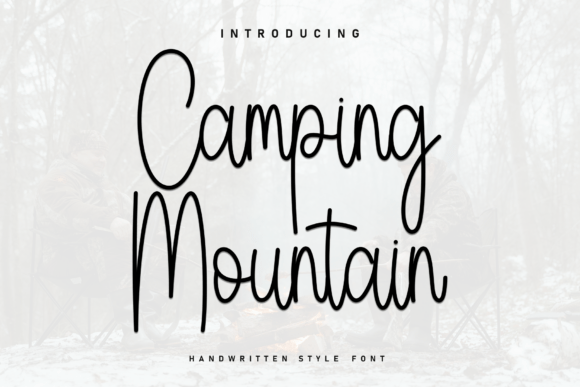
Camping Mountain
Camping Mountain gibi yüksek kaliteli varlıklar arıyorsanız, bu premium paket yaratıcı projeleriniz için harika bir seçimdir.
İster İsteğe Bağlı Baskı (POD) ürünleri, ister düğün davetiyeleri veya sosyal medya grafikleri oluşturuyor olun, Camping Mountain ideal bir uyumdur.